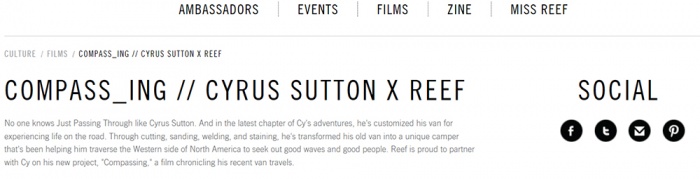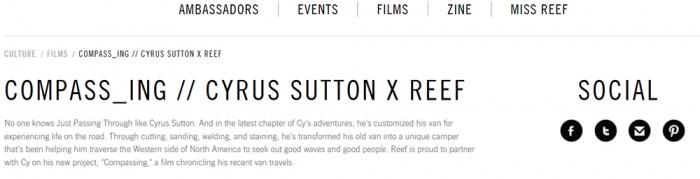
Dünne hohe Schrift wie im Beispiel
Ich bin auf der Suche nach der Schriftart, die auf dieser Website (als Dateianhang ein vergrößertes Bild) verwendet wird:
Hab schon ziemlich viel durchstöbert, bin aber noch nicht wirklich fündig geworden!
Für die Erkennung von Webfonts nutze ich gern Fount, das zeigt dir das Ergebnis sofort an. In deinem Fall sieht das dann so aus:
da es eine website ist die den font nutzt hättest du auch ein stück text markieren können und mit einem rechtsklick (bei firefox) auf »element untersuchen« gehen können, da steht es was für eine schrift da benutzt wird.